Система дополнительных знаков кириллицы: как согласовать точки, штрихи и выносные элементы
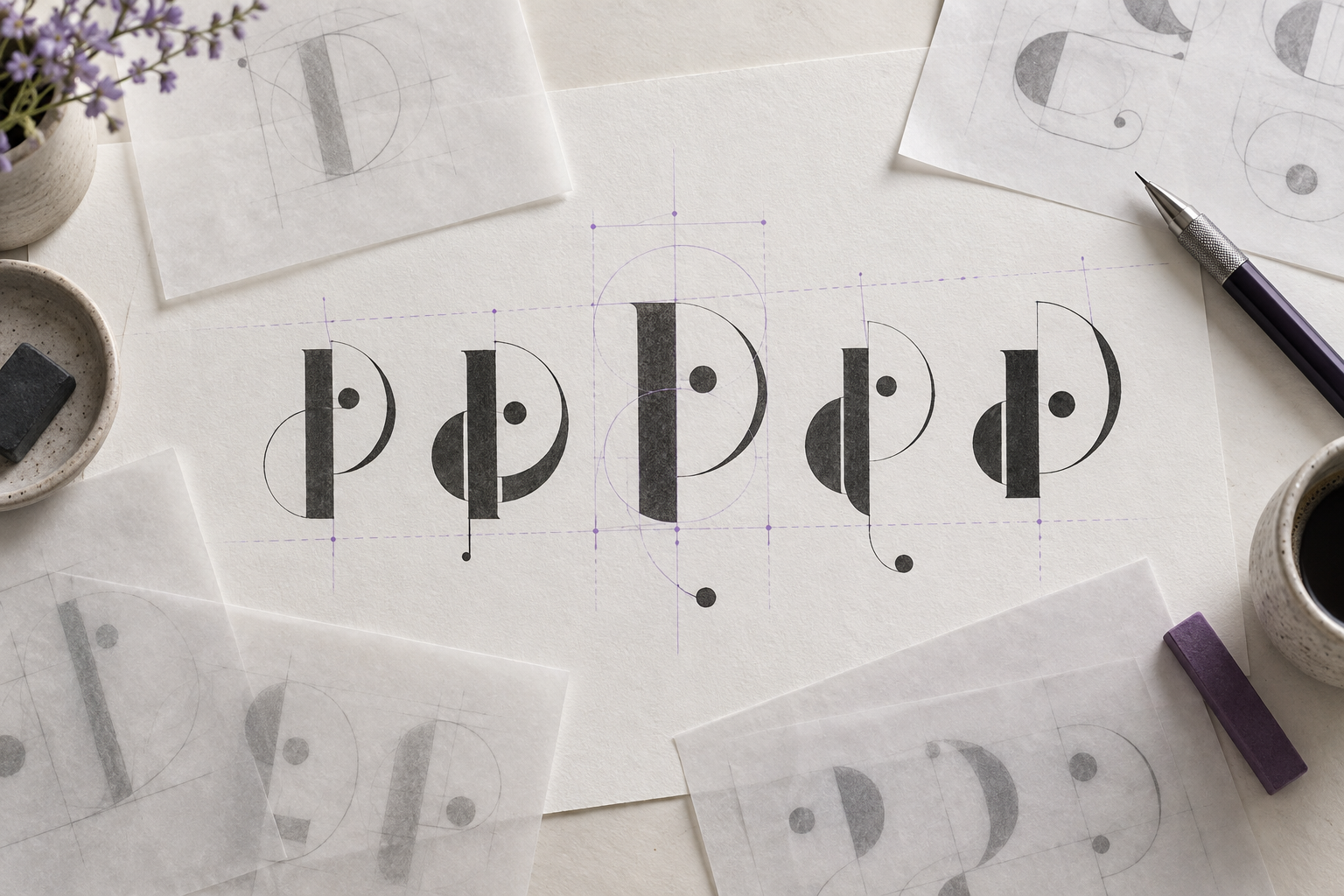
Система дополнительных знаков кириллицы помогает расширить авторский шрифт для нескольких языков и при этом сохранить цельный рисунок. Начните не с копирования базовой буквы, а с правил: как меняются штрих, пропорции, положение диакритики и интервалы. Затем проверьте каждую новую форму в паре с исходной буквой, в словах и после экспорта.
Сначала определите, что именно вы добавляете
Дополнительный знак может быть новой буквой, буквой с отличительным элементом или альтернативным начертанием уже существующей буквы. Внешнее сходство само по себе не решает, какой это случай: текстовая роль и языковая норма важнее впечатления от контура. Unicode кодирует символы, а шрифт задаёт их визуальное представление — глифы. Это различие объяснено в официальной FAQ Unicode о шрифтах и клавиатурах: официальная FAQ Unicode о шрифтах и клавиатурах.
До рисования составьте список поддерживаемых языков и их письменных требований. Для каждого языка выпишите нужные прописные и строчные буквы, варианты диакритики и несколько слов, в которых эти буквы встречаются. Не ограничивайтесь колонкой кода символа: добавьте заметку, чем форма должна отличаться от ближайшей базовой буквы и где этот контраст обязан сохраняться.
Соберите визуальную грамматику до отдельных глифов
У расширенного набора должна быть общая логика, а не одинаковый рецепт. Например, две точки над круглой буквой могут опираться на правила русской ё, а буква с нижним выносом требует другого решения: у неё меняются силуэт, нижняя граница и иногда расстояние до соседей. Определите общие параметры семьи — контраст штрихов, форму окончаний, скругление, наклон, ширину и характер соединений — и отдельно запишите допустимые исключения.
Сделайте маленькую таблицу решений, прежде чем строить десятки контуров. Для каждой группы отметьте базовую форму, тип добавления, место посадки и риск смешения. Эта таблица не заменяет рисунок: она помогает обнаружить противоречие, пока исправление ещё не затронуло весь шрифт.
- Надстрочный элемент: точки, дуга или короткий штрих; проверьте запас до верхнего края строки.
- Перечёркивание или приставной штрих: проверьте, не превращает ли он форму в соседнюю букву.
- Нижний вынос: согласуйте длину, наклон и баланс массы относительно базовой буквы.
- Изменение корпуса: сравните скелет, ширину и просветы, а не только декоративную деталь.
Сравнивайте модифицированную букву с её основой
Положите базовую и дополнительную формы рядом в одном кегле и начертании. Сначала сравните общий скелет: высоту, ширину, наклон, внутреннее пространство и оптический вес. Затем уберите цвет и уменьшите масштаб. Если различие исчезает без увеличения, знак держится на слишком хрупкой детали; если дополнительная буква выглядит тяжелее, проверьте площадь и толщину добавленного штриха.
Не копируйте диакритику только геометрически. Две одинаковые точки на широком и узком основании могут требовать разной оптической посадки: центры остаются связанными с буквой, но видимая пара должна выглядеть уравновешенной. На прописных и строчных формах один и тот же элемент также может быть разного размера. Сохраняйте узнаваемый почерк семьи, а не одинаковую координату во всех контурах.
Полезна контрольная пара «основа — добавочная форма» в обычном и курсивном начертании. Если дополнительный знак наклонён иначе, чем корпус, он кажется приклеенным; если слепо наклонить всё вместе, отдельный элемент может потерять характер. Проверьте обе версии в словах: визуальная разница между двумя глифами ценна только тогда, когда читатель не принимает её за случайную кляксу или дефект скана.
Заложите место для дополнительных форм в метриках
Расширенный знак может выходить за обычную высоту прописных или строчных букв. Надстрочная часть требует свободного поля сверху, а нижний штрих — места под базовой линией. Сначала отметьте эти пределы на контрольной сетке и проверьте их на самых широких и узких основаниях. Если ориентироваться только на габариты русских букв, верхний элемент может столкнуться с диакритикой следующей строки, а вынос — стать причиной тесного межстрочного интервала. Это не повод автоматически увеличивать весь шрифт: сначала убедитесь, что контур и метрики действительно требуют такого изменения.
Сравнивайте не только максимальную высоту, но и то, как новая форма распределяет тёмную массу. Две точки могут занимать небольшой прямоугольник, однако визуально утяжелять верх буквы сильнее, чем длинный тонкий штрих. Для проверки поставьте глиф рядом с обычными круглыми, острыми и вертикальными основаниями. Если одна и та же диакритика на каждом основании выглядит одинаково «прибитой» сверху, измените оптическую посадку, сохраняя узнаваемую форму самого элемента.
Полезно разделить конструктивные параметры и оптические поправки. Конструктивные параметры задают общий принцип: угол штриха, контраст, характер окончания, размер точки. Оптические поправки отвечают за конкретный глиф: сдвиг над узкой формой, раздвижение пары точек или компенсацию у круглого основания. Тогда похожие символы остаются родственными, но система не заставляет их подчиняться одной механической координате.
Если сходные добавочные элементы отличаются по толщине, высоте или оптическому весу сразу в нескольких буквах, проблема обычно в правилах семьи. Сравните группу целиком, зафиксируйте общие параметры и после этого внесите согласованные правки.